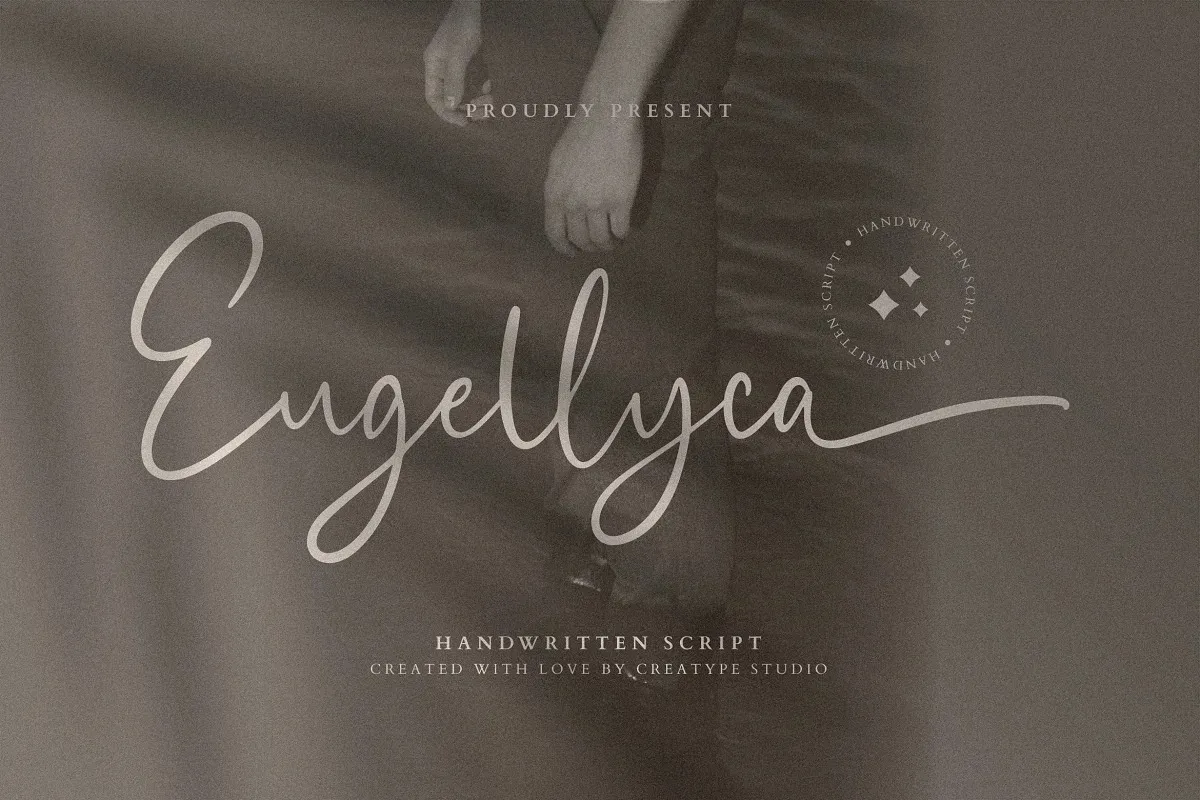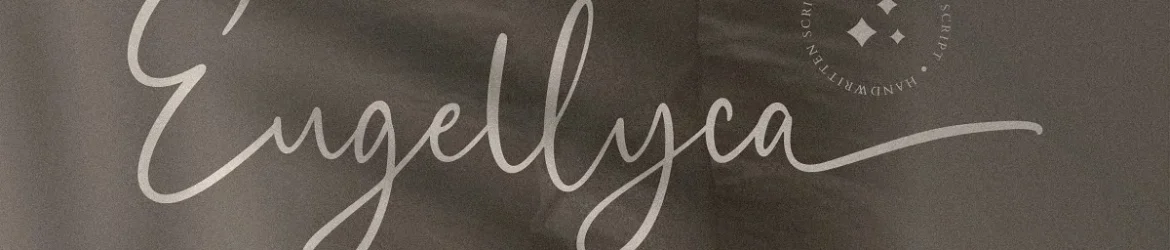
Eugellyca Font – Download Grátis
Esta é uma nova coleção de fontes para escrita a mão criada por Creatype Studio. Se você é designer, influenciador nas redes sociais, blogueiro ou apaixonado pelo estilo jovem e moderno, essa font certamente te agrada. Com um ar delicado e forte ao mesmo tempo, ela combina perfeitamente com uma fonte serif ou sans-serif em maiúsculas, como a que você pode ver no preview acima. Seja para criar posts de Instagram atrativos, blogs cheios de personalidade ou até mesmo produções de vídeo pessoais, essa font oferece um toque sofisticado e atual. Suas linhas elegantes e suas letras femininas e vivas são perfeitas para quem deseja transmitir uma mensagem fresca e inovadora. É ideal tanto para designers que buscam dar vida aos seus trabalhos quanto para amantes de moda, querendo traduzir seu estilo único em um design visual irresistível. A Eugellyca Font é um recurso atraente para qualquer designer que deseja adicionar um toque especial às suas criações digitais. Ela oferece flexibilidade e versatilidade para criar uma variedade de looks gráficos, mantendo o seu estilo único ao mesmo tempo. Não deixe de experimentar essa fonte vibrante para dar vida a seus projetos!